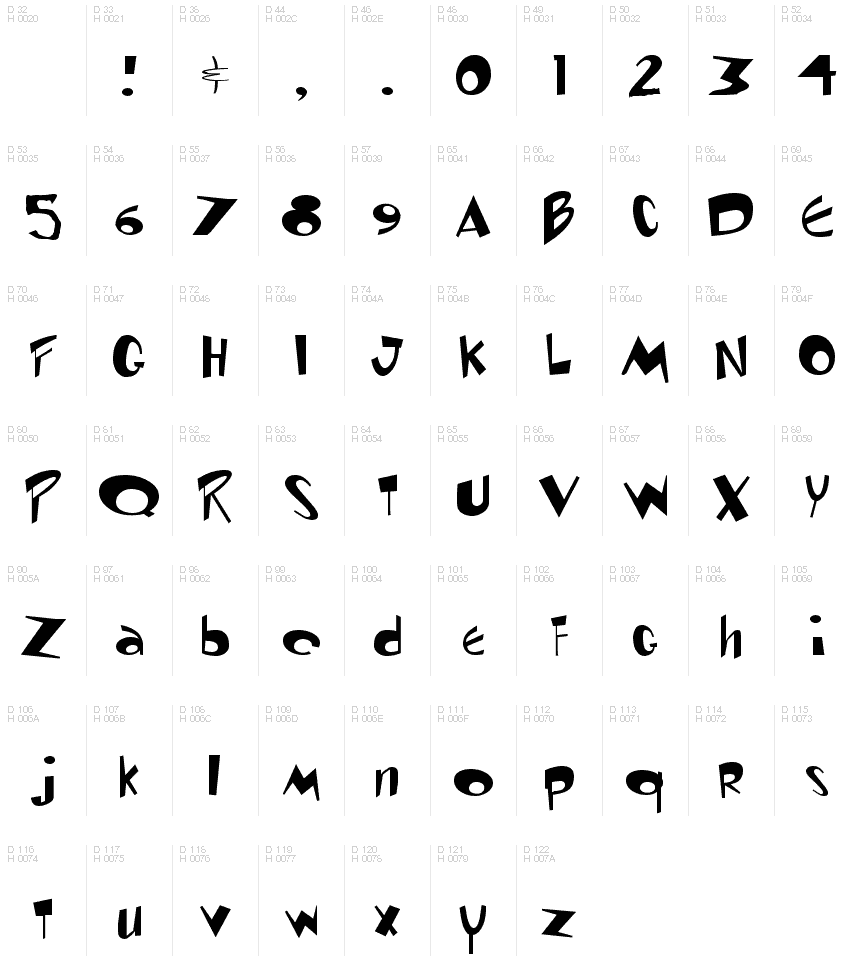
Ren & Stimpy to darmowy krój pisma w stylu cartoon od Ren and Stimpy, który stawia na elastyczny, "gumowy" wygląd, ręczne wykończenie oraz rozciągnięte, nieco krzywe formy. Litery sprawiają wrażenie niepokornych, łącząc ostre kąty z szerokimi łukami – całość przypomina bardziej napisy z klasycznych kreskówek niż grzeczne fonty komiksowe. Dzięki temu ten darmowy font świetnie sprawdza się w animowanych planszach tytułowych, nagłówkach plakatów, okładkach zinów, grafikach na merch czy odważnych eksperymentach z logotypami, gdzie nieszablonowy rytm robi największe wrażenie. Idealny do krótkich haseł i brandingu opartego na wyrazistych postaciach, ponieważ nadaje każdemu słowu energię ręcznie rysowanego żartu.
Ren & Stimpy